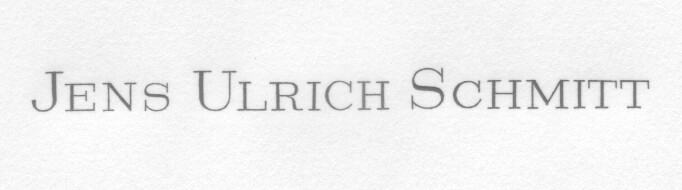
hat jemand eine Idee um welche Schriftart es sich bei diesem Text handeln könnte?
Nicht gleich, aber ähnlich:
Ich vermute, dass das von Hand gestochen wurde. Die unterschiedlichen C und H deuten darauf hin.
Danke, ja das ist handgraviert. Die Elspeth war auch die ähnlichste die ich gefunden habe.